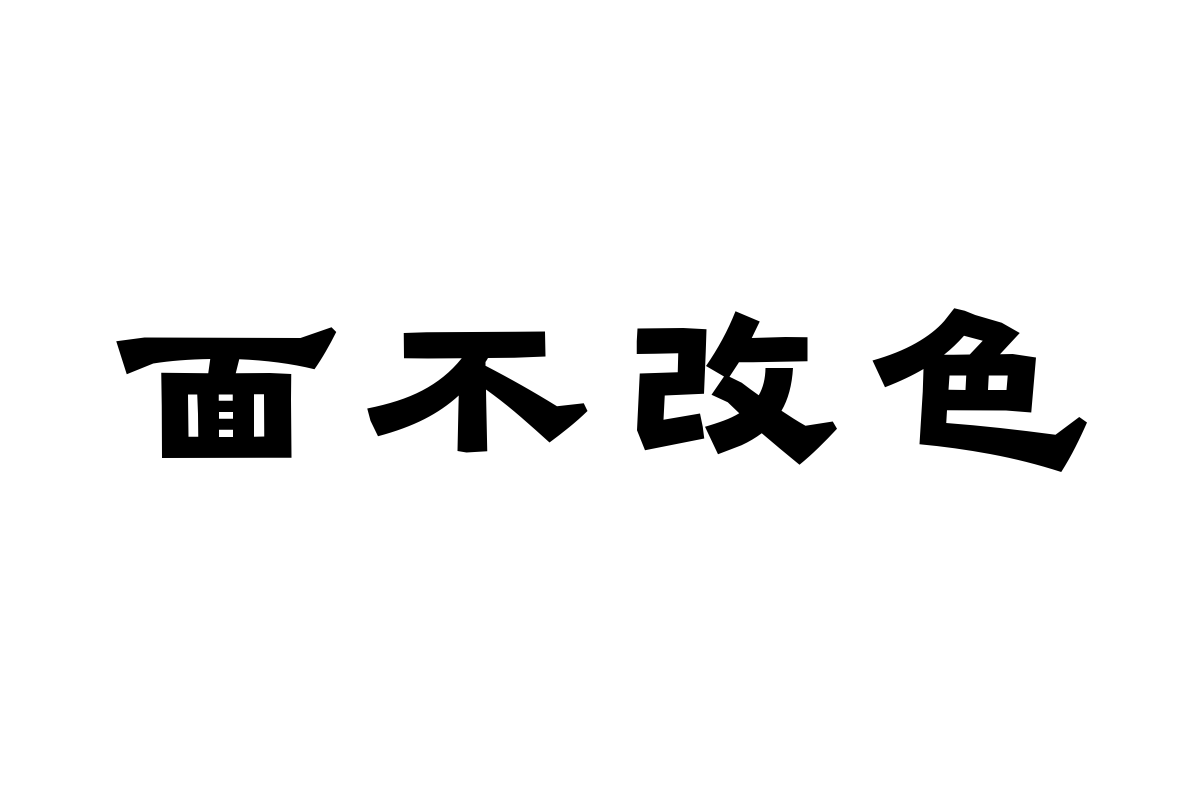
汉仪金石繁体字体是一款由汉仪公司设计开发的中文字体。这款字体以其独特的设计风格和丰富的艺术感而受到广泛欢迎,适用于各种需要强调文字美感和艺术氛围的场合。
汉仪金石繁体字体的特点主要体现在以下几个方面:
1. 字形结构独特:汉仪金石繁体字体采用了传统的书法风格,字形结构紧凑而富有层次感。每个字都经过精心设计,使得整体视觉效果更加和谐统一。
2. 笔画流畅自然:汉仪金石繁体字体的笔画流畅自然,没有生硬的感觉。无论是横、竖、撇、捺等基本笔画,还是复杂的组合笔画,都能展现出优美的线条美。
3. 艺术感强烈:汉仪金石繁体字体具有很强的艺术感,适合用于需要突出文字美感的场合。例如,在广告设计、书籍封面、网页设计等方面,都能展现出独特的艺术魅力。
4. 可定制性强:汉仪金石繁体字体支持个性化定制,用户可以根据自己的喜好和需求,对字体的字形、字号、颜色等进行个性化设置。这使得汉仪金石繁体字体更加符合个人需求和使用场景。
总之,汉仪金石繁体字体是一款具有独特设计风格和丰富艺术感的中文字体。无论是用于商业设计、教育出版还是其他场合,都能展现出其独特的魅力和价值。